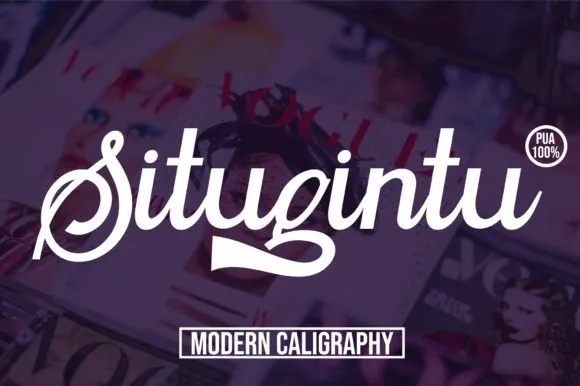
A “Situgintu Font” é uma atraente fonte script desenvolvida pela Fallengraphic. Inspirada nos antigos ensaios de caligrafia, esta fonte traz um delicado e agradável ar ambiente junto com formas perfeitas e equilibradas. Não é excessivamente fina nem grossa; mantém-se levemente mais delgada e tem uma variabilidade que o torna único e criativo. Esta elegante fonte foi projetada para destacar o encanto e a beleza de seus projetos, perfeitamente adaptável às diversas aplicações gráficas. Como uma fonte script, ela oferece flexibilidade para diferentes texturas e ambientes digitais, tornando-a um recurso valioso para designers em busca de personalidade e expressão única nos seus trabalhos.